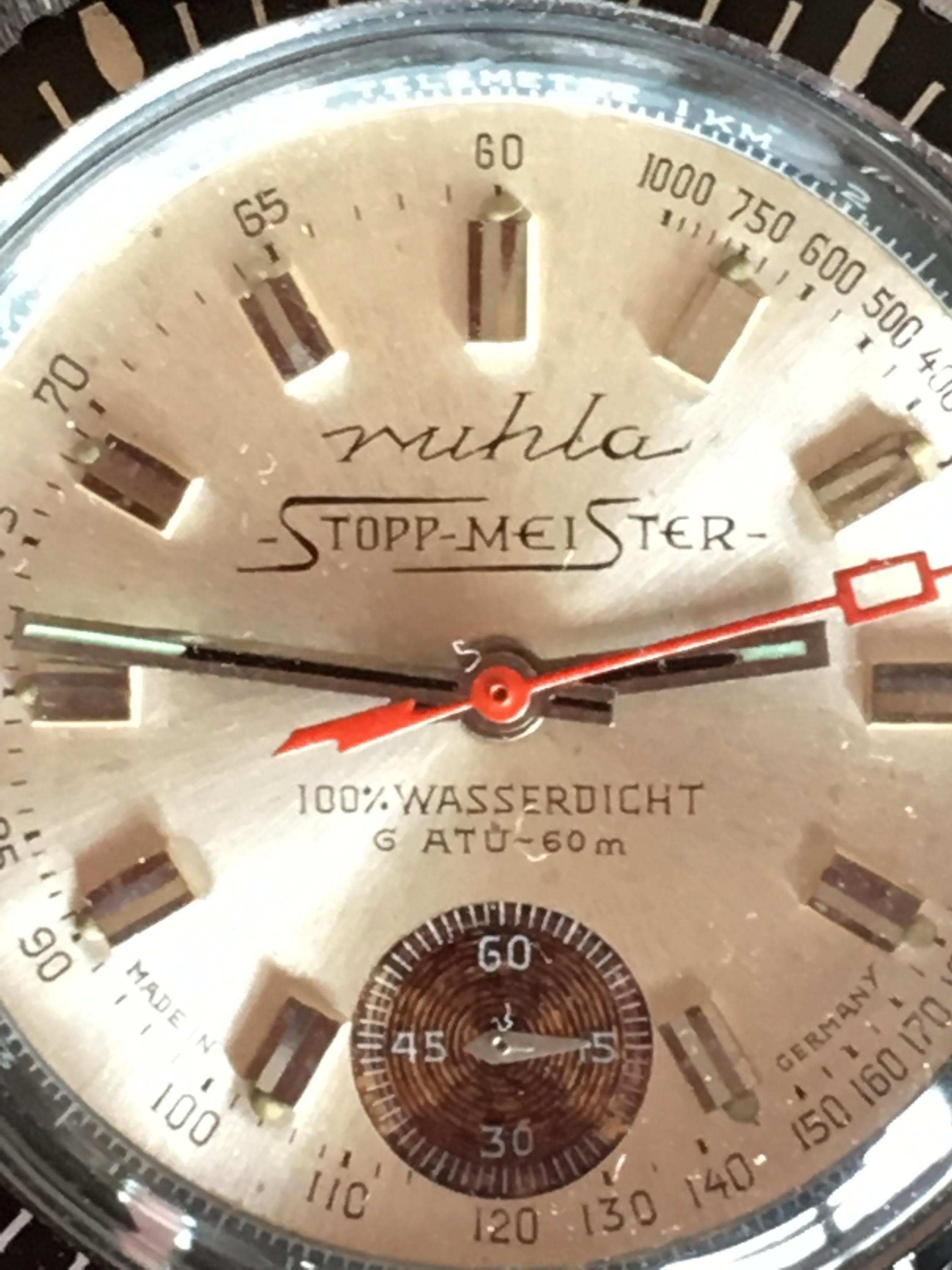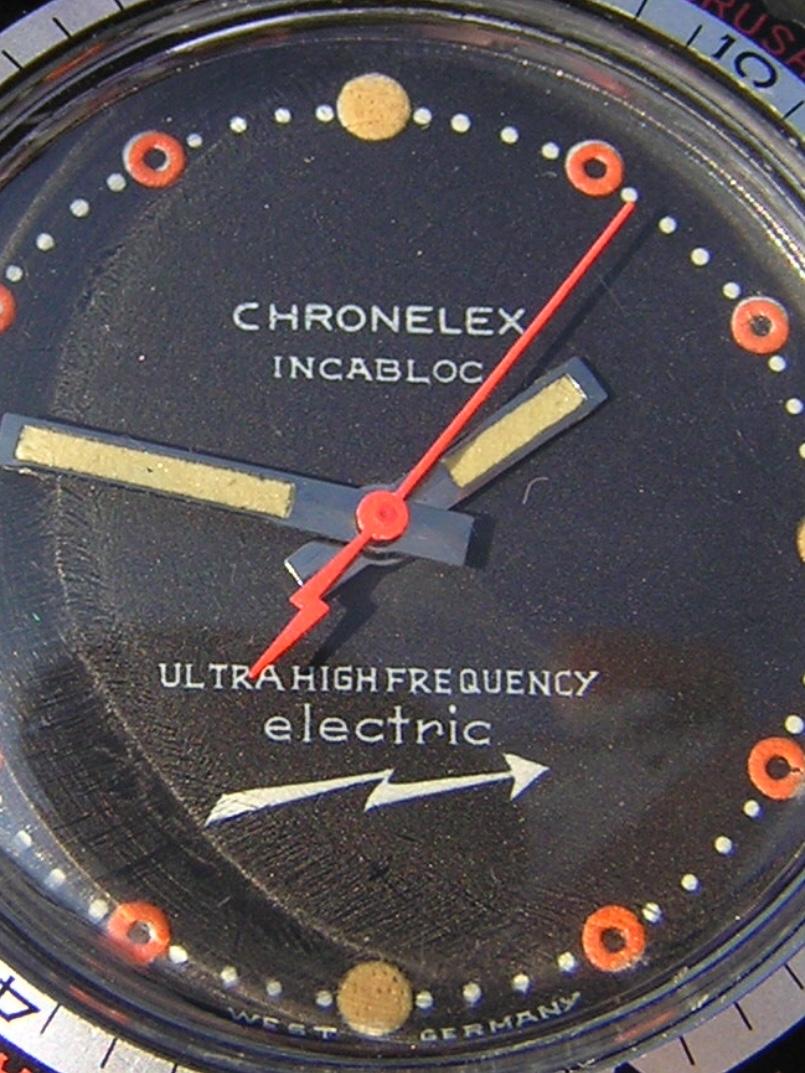
Schrift der Exportuhren von Ruhla / DDR
Ich erfhoffe mir Hilfe bei der Identifizierung der auf den Zifferblättern der Ruhla-Exportuhren verwendeten Schriftart. Ich kann folgendes beitragen. Die auf den Fotografien abgebildeten Zifferblätter wurden zwischen 1969 und spätestens 1973 hergestellt. Den Begriff Stopp-Meister gibt es nach 1973 nicht mehr. Zumindest für den Stopp-Meister gibt es Aussagen, dass die Zifferblätter in der BRD gefertigt und die Uhren in Ruhla lediglich konfektioniert wurden. Eine weitere bisher nicht durch Quellen eindeutig belegbare Aussage besteht darin, dass der Begriff „Stopp-Meister“ durch die Firmen Quelle (Vertrieb) und Rexer (Importeur) kreiert sei. Es bleibt offen, ob bei entsprechendem Wahrheitsgehalt dieser Aussage, auch das Schriftdesign vorgegeben wurde. Der Ruhla-Schriftzug des Stopp-Meister weicht vom zum gleichen Zeitpunkt in der DDR verwendeten Ruhla-Schriftzug ab.
Herr Herrmann, danke für die schnelle Antwort. Da weiß ich jetzt garnicht, ob ich mich beschämt in eine Ecke zurückziehen soll oder lieber doch noch auf eine Antwort warte, die mir Auskunft darüber gibt, aus welchem Font denn die Buchstaben auf den Zifferblättern entlehnt sein könnten. Mitgeht es nicht um die Markenzeichen sondern um die sonst auf den Zifferblättern verwendete Schrift (z.B. Made in Germany). Das hätte ich besser ausführen sollen. Der Hinweis mit dem Unterschied im Ruhla-Logo sollte mehr die unausgesprochene Vermutung darlegen, dass die Schrift nicht unbedingte ihren Ursprung in der DDR haben muss.
Nein, beschämt in die Ecke muss man nicht, sondern einfach nur akzeptieren, das neue Schriften, die ein Schriftgestalter entwirft nicht aus einer anderen Schrift entlehnt sein müssen.
Und die bekannten Schriftgestalter haben eben nicht nur komplette Schriften entworfen, sondern eben auch, dann als Grafiker nur kurze Schriftzüge, bei denen man dann als Schriftgestalter noch mehr Freiheiten hat, müssen sich dann in der gewählten Formensprache eben nicht alle Buchstaben des Alphabets umsetzten lassen.
Umgekehrt ist es nicht selten, dass sogar ein Logoauftrag bei einem auf Schriftgestaltung spezialisierten Grafiker hinterher dann eine ganze Schrift draus geworden ist.
Die Frage hier, welchem Font denn die Buchstaben für die Zifferblatt-Texte entlehnt wurden, wäre das gleiche, als würde man fragen, aus welchem Font Adrian Frutiger denn  die Buchstaben für die Univers entlehnt habe.
Man könnte hier aber umgekehrt durchaus nach modernen digitalen Schriften fragen, die den gezeigten Beispielen in der Form ähnlich sind. Eine solche Suche kann von Erfolg gekrönt sein, denn so mancher heutige Schriftgestalter hat sich von schönen alten Schriftzügen zu neuen digitalen Schriften inspirieren lassen.
»Genau diese Schrift« wird man, wie oben von den Kollegen bereits fachkundig ausgeführt, nicht als digitale Variante finden, aber eine ähnliche Schrift, die den gewünschten Formencharakter aufgreift, mag sich mit etwas Durchhaltevermögen und Glück finden lassen.
Das akzeptiere ich mit Sicherheit und falls auf meine Vokabel „entlehnt“ in Bezug auf die Schrift angesprochen wird, damit meine ich lediglich deren Verwendung, nicht was ähnliches nachmachen oder darin eine Inspiration für was Neues finden. Ich habe also davon auszugehen, das die Schrift keinen „Namen“ hat. Ich weigere mich aber zu glauben, dass sie nicht in irgendeiner Form normiert war oder zumindest als irgendeine Art Muster geschützt war / ist.
Die Schrift und ich verweise hier noch einmal auf das Wort „Germany“, ist sowohl auf der in der DDR als auch in der in der BRD gefertigten Uhr identisch. Die Logos interessieren mich weniger, da trifft der Artikel, auf den Herr Herrmann hinwies.
Der Artikel behandelt aber nicht nur Logos. Geräte-Beschriftungen sind auch dabei und ein Wecker als Beispiel. Die Beschriftung einer Uhr fällt exakt in diese Kategorie.
Das Wort Germany in dem Beispiel oben ist (physisch) so klein – da gibt es letztlich nichts gestalterisch zu schützen. Das is an der unteren Grenze zu Lesbarkeit. Für schutzwürdige Gestaltung ist da genauso wenig Platz, wie für eine Normzeichnung oder ähnliches.
Ich habe mal versucht, die drei besonders typischen Buchstaben von Germany auf beiden Zifferblättern nachzustellen. Eine Font-Suche mit diesen Formen., insbesondere mit dem an ein kyrillisches U erinnernde Y brachte kein Ergebnis:
Ich denke, dass in vordigitalen Zeiten Zifferblätter als kompletter Entwurf gezeichnet und dann entsprechend umgesetzt wurden. Die gezeichneten Schriften unterlagen dabei der gestalterischen Freiheit der Urheber dieser Entwürfe. Eine dabei im Laufe der Zeit ausgeprägte gestalterische Handschrift verhalf den Uhren, neben anderen Designmerkmalen, zu einer visuellen Markenidentität. Insofern wundert mich nicht, dass bei den verschiedenen oben gezeigten Zifferblättern bestimmte (typo)grafische Details übereinstimmen – was bei den Kunden (und/oder dem Gestalter) beliebt war, wurde logischerweise beibehalten.
Mir ging es auch nicht darum, ob eine digitale Variante der Schrift existiert. Ich wollte die Schrift für einen Aufsatz über die Exportuhren von Ruhla lediglich genau bezeichnen können. typografie.info wird von der Fachwelt gelobt, kommt aus Weimar. Und weil die Uhrenwerke Weimar seit 1967 zum VEB Uhrenkombinat Ruhla gehörten, eine Menge Design-Elemente auch aus Weimar stammten, assoziierte ich eine gewisse Nähe und erhoffte mir eine schnelle Antwort. Die offensichtlich für das Design, zumindest des Stopp-Meister, verantwortlich zeichnende Firma wurde 1994 liquidiert, Nachfrage also aussichtslos. Es gibt einen Hinweis auf eine Ziffernblattfertigung in Pforzheim. Die Recherche dazu dauert noch an. Mir war nur aufgefallen, dass bei vielen Exportuhren von Ruhla um 1970 herum bei Erläuterungen der auf dem Zifferblatt aufgedruckten Eigenschaften wie z.Bsp. zur Wasserdichtigkeit oder bei der Herkunftsbezeichnung, die auf den Fotos abgebildete Schrift zu finden war.
Diese Vorgehensweise hatte natürlich auch einen Vorteil, der durch die Allgegenwärtigkeit digitaler Schriften praktisch verloren gegangen ist: Damals waren diese Branchenspezifischen Schriften auf die speziellen Bedürfnisse der Anwendung und des zu beschriftenden Materials abgestimmt, während heute oft Schriften, die für den Druck auf Papier gedacht waren eingesetzt werden, während diese Musterzeichnungen mit den gänzlich andersartigen Schriften beim Umstieg auf moderne Beschriftungsmethoden oft vernichtet wurden, und so verloren gingen.